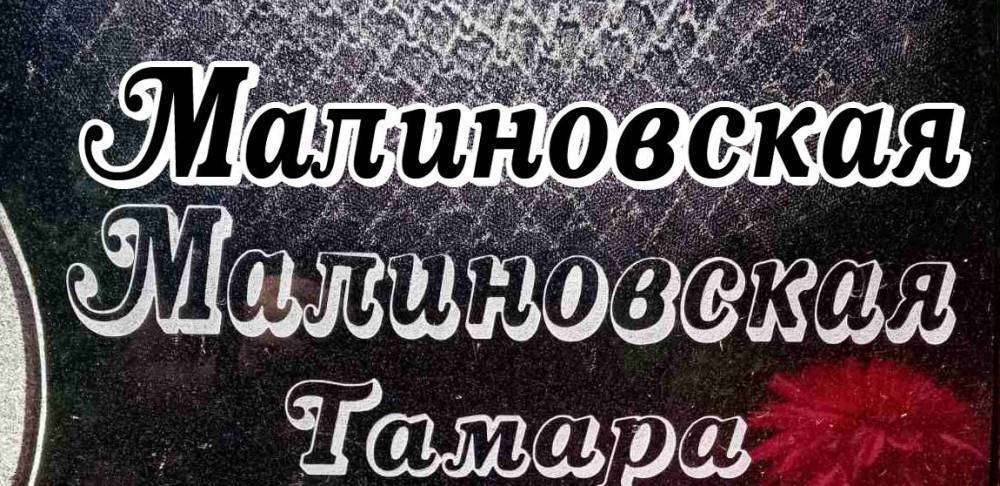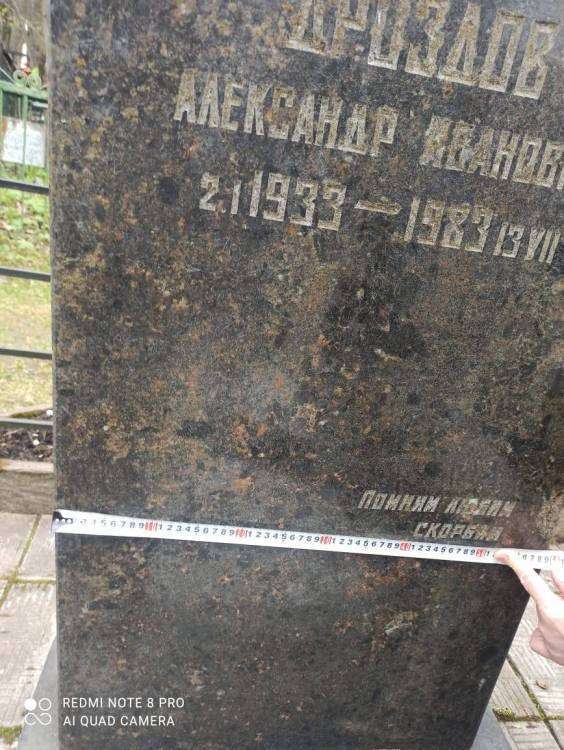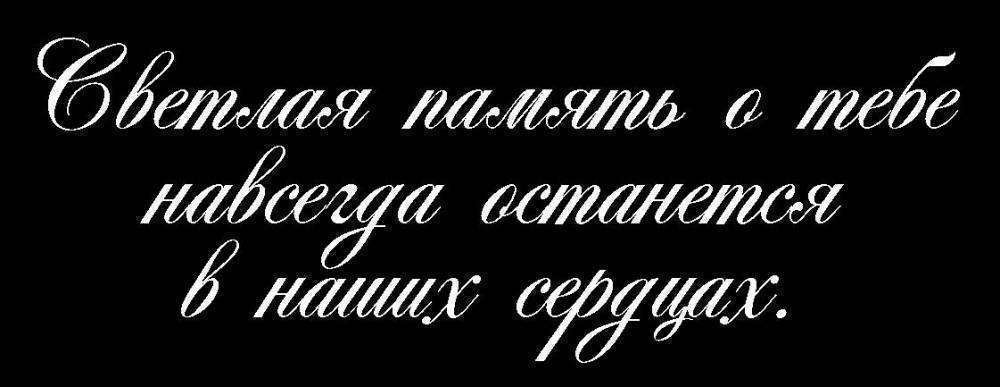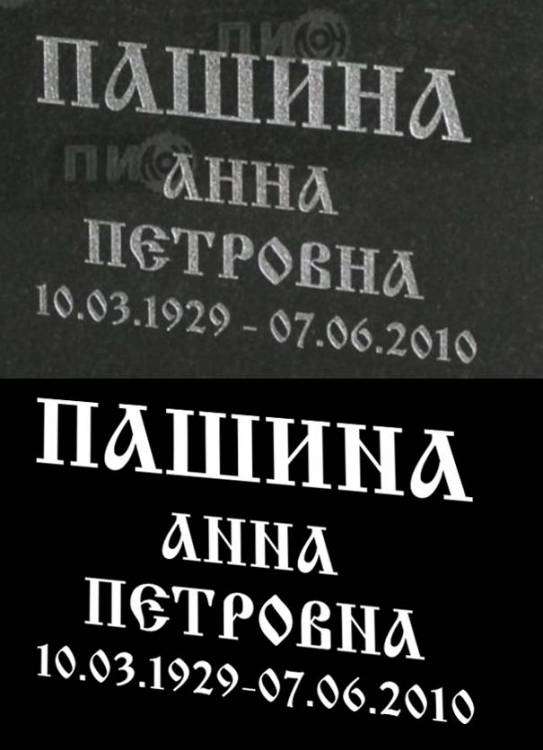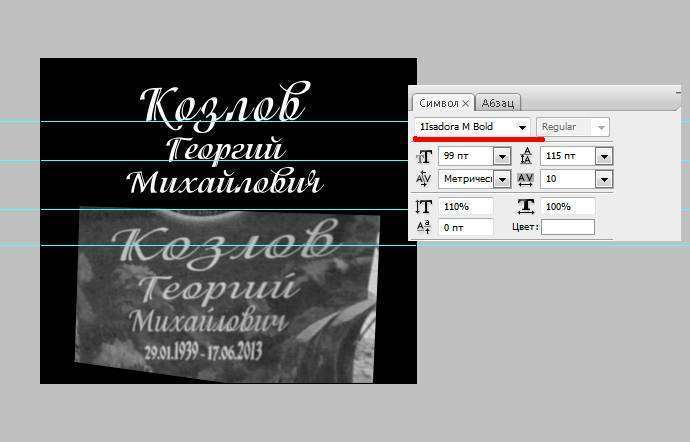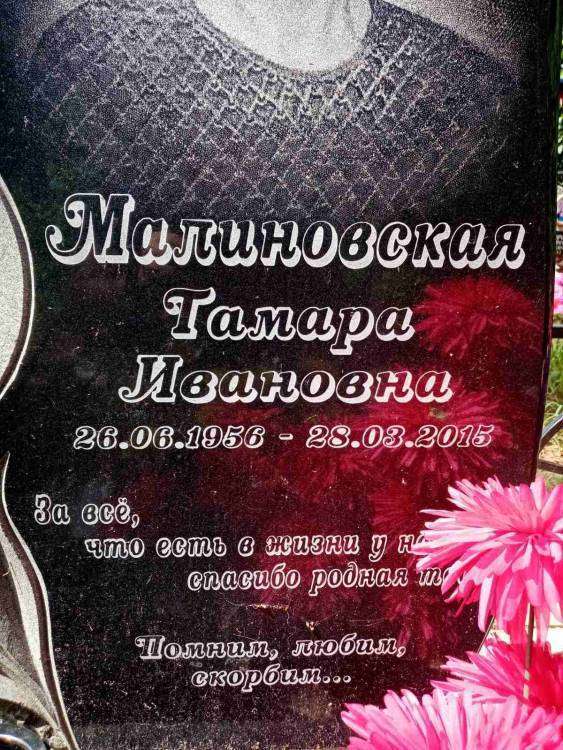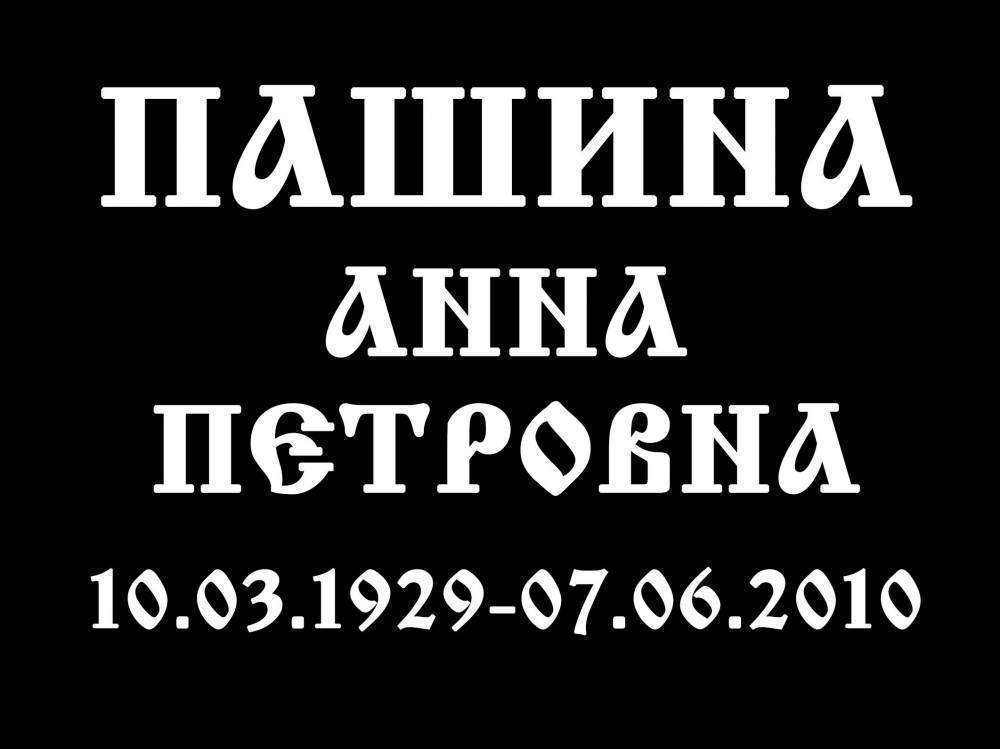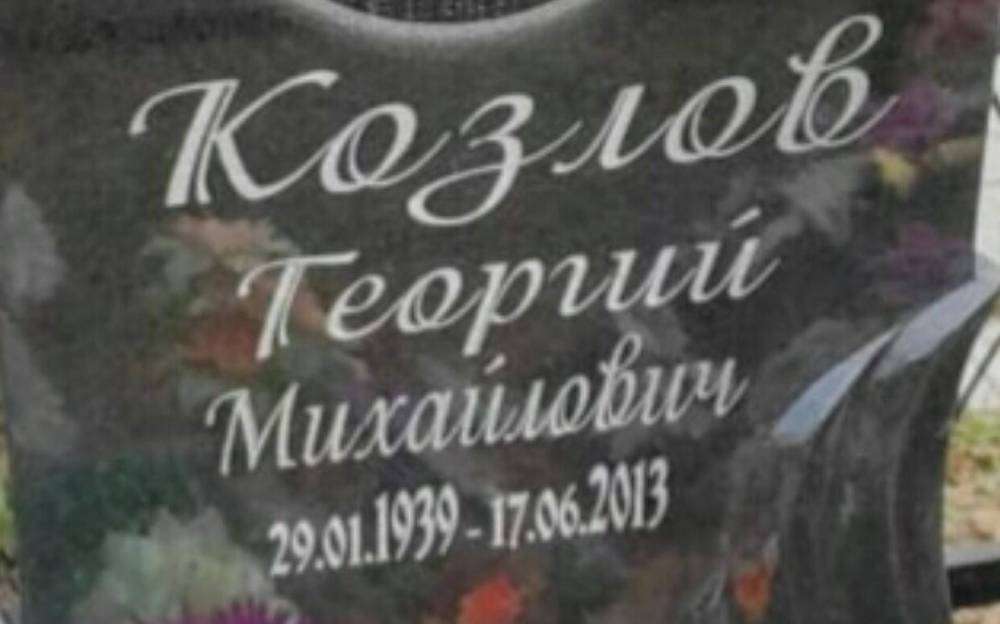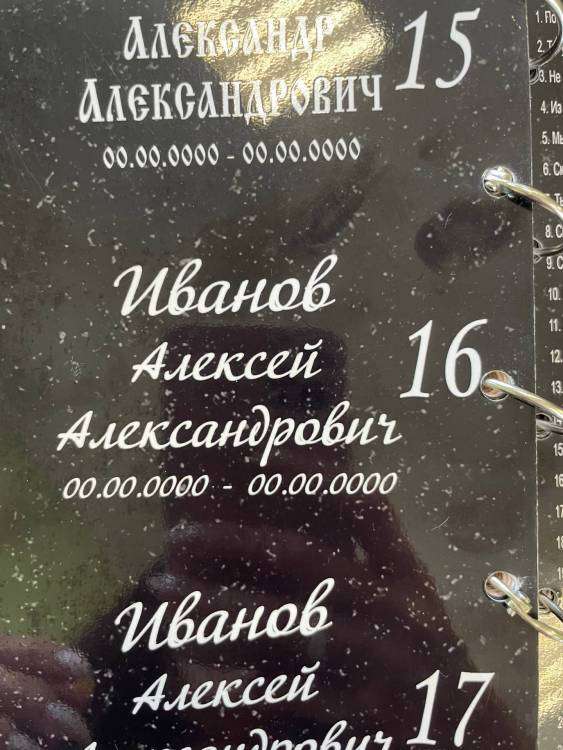
Помогите найти шрифт!
@Aidar606 Caslon Bold
Заглавные
Добрый день уважаемые.
Ищу вот такой шрифт,может кто подскажет где можно будет его скачать, заранее благодарю
И всё-таки это не ижица, а CyrillicOld
Это Ижица, не надо сбивать с толку. Просто перекладина на букве Н подправлена
О чем спор, если ижица и Cyrillic Old по сути один и тот же шрифт, с разницей в перекладине Н и остроте засечек, которые сразу и не заметишь ну и в ижице есть начертания букв, как в ирмологионе, которые не нужны...
Зачем тогда набирать ижицу, если ее еще и править надо?
Ребят, подскажите, что за шрифт такой?
@Nigozero Coronet
Вот и я со шрифтом разобраться не могу.
Кому знакома эта каллиграфия?
Судя по всему - Country Western Swing Black
Что-то только он во все стороны пляшет на стеле :aag:
Он самый и есть.
А пляшет текст... Станок наверное спиртом протирали :biggrin:
Портрет набит вручную, возможно и текст распечатали на бумаге, а потом вручную гравировали...
Доброго дня всем. Не могу определить шрифт, очень похож на Есенин, но не он. Помогииите пожалуйста))
Antonella script Regular
Блин, что то мне похожее попадалось на сайтах со шрифтами...
Это есть PG Isadora Cyr Pro
@dargin61 , согласен с @SARATON .
Помогите пожалуйста найти похожий шрифт
Здравствуйте!Помогите с названием шрифта🙏
@ЯнаРом посмотрите  Allegretto Script One, если не ошибаюсь.
Не, не он :(